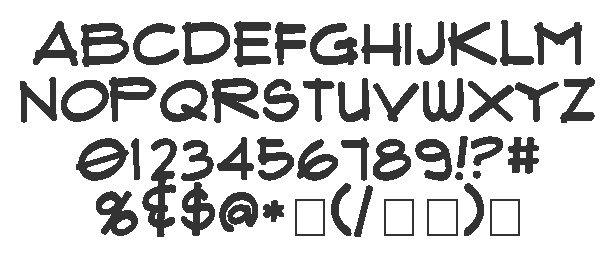
Font Flux Architect Việt hóa là bộ phông chữ kỹ thuật mô phỏng chuẩn xác phong cách viết chữ hoa tay bằng bút kim và bút chì kim của các kiến trúc sư trên bàn vẽ đồ án truyền thống. Nổi tiếng với các nét chữ dứt khoát, độ nghiêng nhẹ nhàng có kỷ luật và tỷ lệ hình học rõ ràng, Font chữ Kiến trúc viết tay này là chất liệu trực quan tuyệt vời để tái hiện cảm xúc chân thực của các bản phác thảo ý tưởng, ghi chú chi tiết kết cấu trong AutoCAD hay mặt bằng phân khu nhà lắp ghép.
Nét bút chì kỹ thuật và nhịp điệu đồ họa của font Flux Architect Việt hóa
Điểm cuốn hút của font Flux Architect Việt hóa nằm ở sự kết hợp giữa tính tự do của chữ viết tay và độ chuẩn xác của tiêu chuẩn vẽ kỹ thuật xây dựng. Các con chữ sở hữu nét gạch dứt khoát ở phần chân, đầu nét có độ nhấn nhẹ tự nhiên mô phỏng lực tì ngòi bút của người thợ vẽ, loại bỏ sự vô cảm của các phông chữ in ấn máy móc thông thường.
Sự ổn định về mặt thị giác của dòng font này giúp bản vẽ phối cảnh toát lên vẻ ngoài sống động, mang đậm dấu ấn lao động sáng tạo của người làm nghề. Khi xuất hiện trên các bề mặt vật liệu kiến trúc như giấy can phác thảo, bảng vẽ kỹ thuật nền xanh, biển chỉ dẫn gỗ mộc hay vách kính dán decal trong các văn phòng container, Flux Architect tạo nên sự hòa quyện thẩm mỹ vô cùng ăn ý.
| Phân loại phong cách | Architectural Lettering / Drafting Sans / Technical Handwritten |
| Mục đích phù hợp | Ghi chú bản vẽ kỹ thuật, phối cảnh phác thảo, sơ đồ mặt bằng |
Tư vấn từ chuyên viên: Flux Architect sở hữu cấu trúc chữ dạng All-Caps dễ đọc. Để bản vẽ đạt hiệu quả thẩm mỹ tốt, bạn nên sử dụng phông chữ này cho toàn bộ các ghi chú kích thước, chú thích vật liệu và tên các phòng chức năng.
03 Ứng dụng Font chữ Kiến trúc viết tay vào thực tế công trình
Nhờ vẻ ngoài chuẩn mực và tính gợi cảm xúc nghề nghiệp sâu sắc, bộ phông chữ này mang lại giá trị thực tế lớn trong khâu trình bày các giải pháp xây dựng hiện đại:
- Ghi chú kích thước và Vật liệu trên Bản vẽ AutoCAD: Những nét chữ viết tay kỹ thuật của Flux Architect giúp các dòng chú thích panel cách nhiệt, dầm thép hộp hay chi tiết liên kết bu lông hiển thị rõ ràng, giúp đội ngũ thi công tại hiện trường nắm bắt thông tin nhanh chóng.
- Trình bày Bìa hồ sơ Phối cảnh Ý tưởng: Phông chữ này khi đặt trên nền phối cảnh 3D phác thảo nét chì sẽ mang lại cảm giác công trình đang được nghiên cứu kỹ lưỡng, tạo niềm tin lớn với các chủ đầu tư yêu chuộng tính sáng tạo nguyên bản.
- Biển chỉ dẫn và Sơ đồ phân khu tại Văn phòng Container: Bạn có thể dùng phông chữ này để in trên các tấm kim loại sơn tĩnh điện hoặc bảng mica mờ, mang lại diện mạo ngăn nắp và tinh thần kiến trúc cho không gian làm việc.
03 Lưu ý bố cục font Flux Architect luôn gọn gàng và chuẩn xác
Để khai thác hiệu quả vẻ đẹp của dòng font chữ kỹ thuật này mà không làm rối mắt bản vẽ, người thiết kế nên lưu tâm một số kinh nghiệm sau:
- Duy trì khoảng cách dòng chuẩn mực: Với cấu trúc chữ hoa kỹ thuật, bạn nên thiết lập khoảng cách dòng ở mức vừa vặn (khoảng 1.3 – 1.4 lần cỡ chữ) để các dòng chú thích không bị dính nét, giữ được nhịp điệu đọc rõ ràng.
- Kiểm soát tỷ lệ chữ trên các tỷ lệ bản vẽ khác nhau: Trong AutoCAD, hãy sử dụng tính năng Annotative Text để chiều cao phông chữ tự động điều chỉnh tương thích với các khung nhìn tỷ lệ 1/50, 1/100 khi xuất bản vẽ in ấn khổ lớn.
- Lựa chọn gam màu đơn sắc mực vẽ: Flux Architect phát huy hiệu quả thị giác cao khi phối cùng màu đen mực kim, trắng nét vẽ kỹ thuật hoặc xanh dương blueprint truyền thống, làm nổi bật đường nét dứt khoát của bộ chữ.